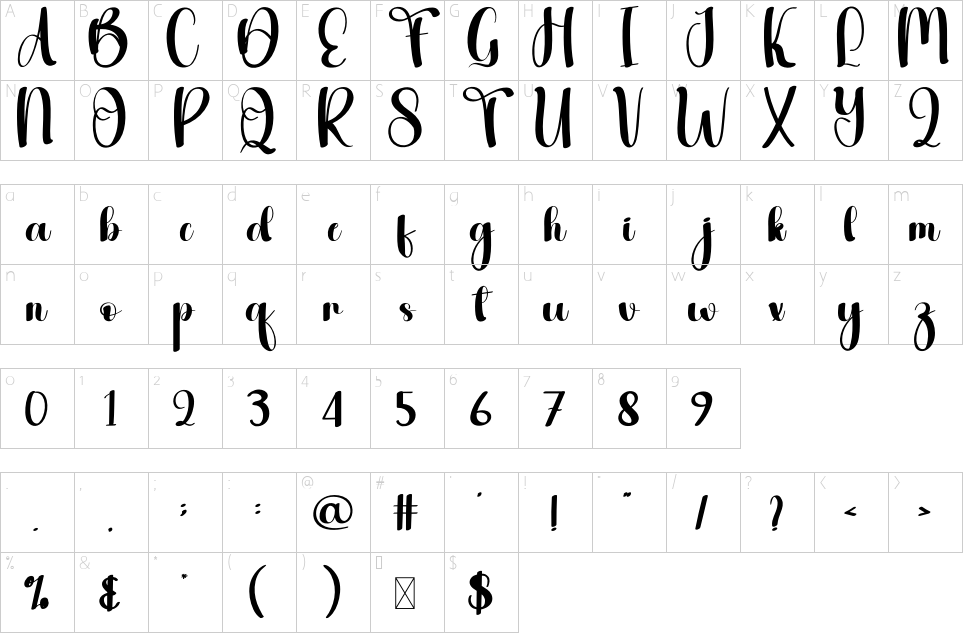
A fonte ‘Journal Font’ é uma opção versátil para designers e escritores de todos os níveis, especialmente aqueles que buscam um estilo de escrita limpo e elegante. Desenvolvida por um designer não especificado, essa fonte vem com 503 downloads, mostrando sua popularidade entre os criadores de design. O Journal Font foi projetada para garantir uma experiência de leitura fluida, oferecendo uma combinação perfeita de legibilidade e sofisticação. Perfeita para aplicações como letras do blog, design de logotipo ou criação de flyers, essa fonte traz uma dose de estilo sem se afastar muito do conforto do texto de leitura. Compre o Journal Font para adicionar um toque de personalidade ao seu design, e certifique-se de que todos os seus trabalhos de design sofram um tratamento único.